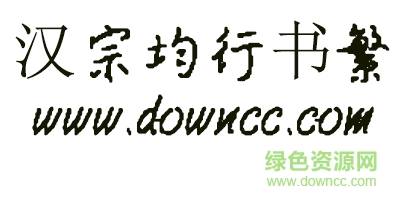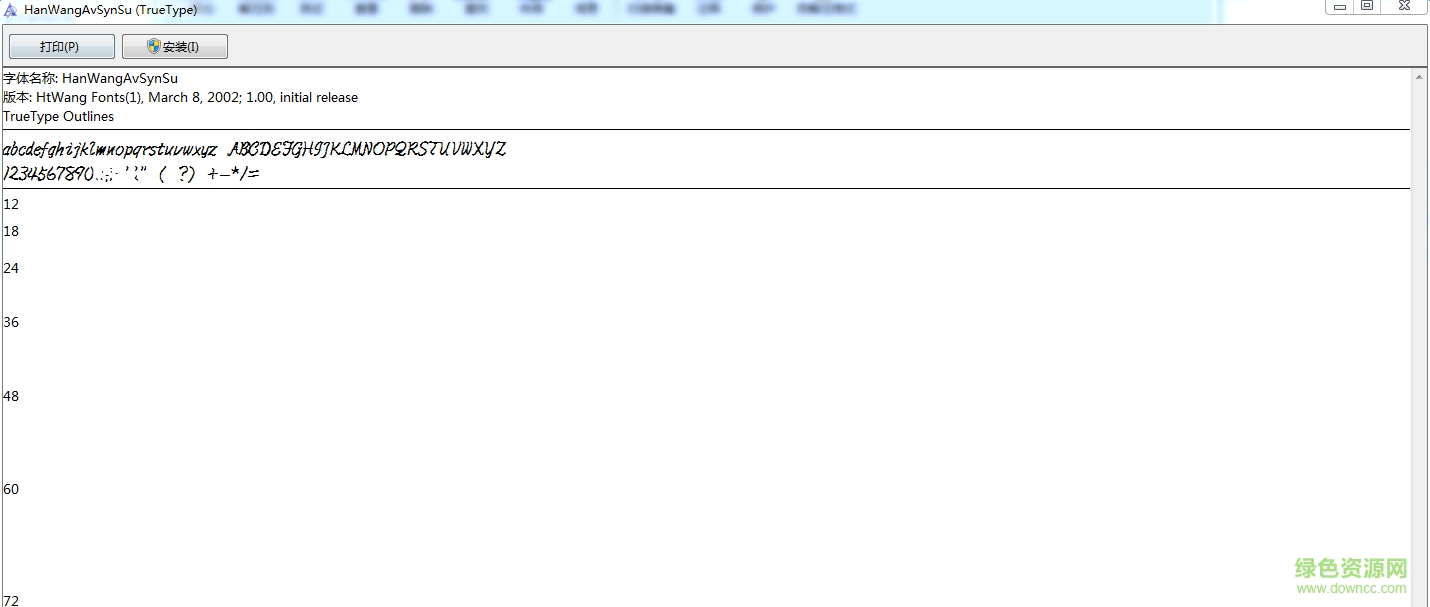
王漢宗均行書繁體風格很獨特,是行書字體中比較突出的一款字體。在進行ps設計、word文字排版的時候可以用得到。支持Win7、Win 8等系統(tǒng)!歡迎大家下載使用。
王漢宗均行書繁是一款王漢宗類行書字體,字體效果比較正規(guī),喜歡行書體字的朋友可以來綠色資源網(wǎng)下載使用看看效果如何。
行書是一種統(tǒng)稱,分為行楷和行草兩種。它在楷書的基礎上發(fā)展起源的,介于楷書、草書之間的一種字體,是為了彌補楷書的書寫速度太慢和草書的難于辨認而產(chǎn)生的?!靶小笔恰靶凶摺钡囊馑迹虼怂幌癫輹菢恿什?,也不像楷書那樣端正。實質(zhì)上它是楷書的草化或草書的楷化??ǘ嘤诓莘ǖ慕小靶锌?,草法多于楷法的叫“行草”。行書實用性和藝術性皆高,而楷書是文字符號,實用性高且見功夫;相比較而言,草書則是藝術性高,但是實用性顯得相對不足。